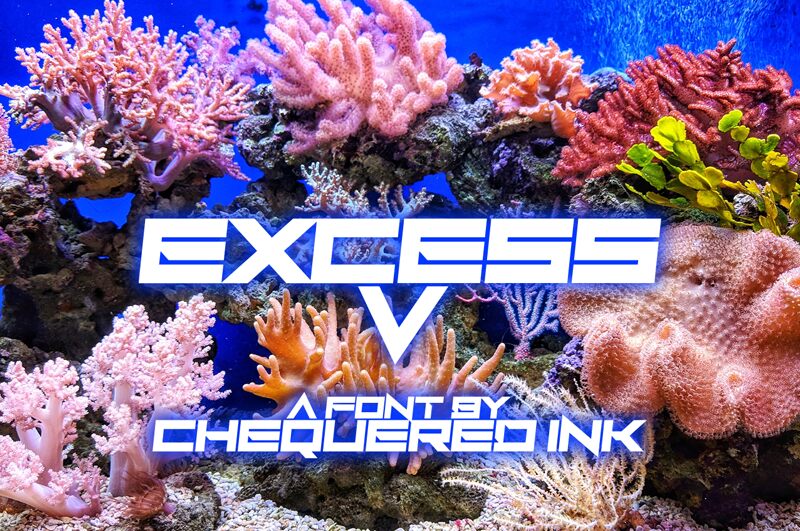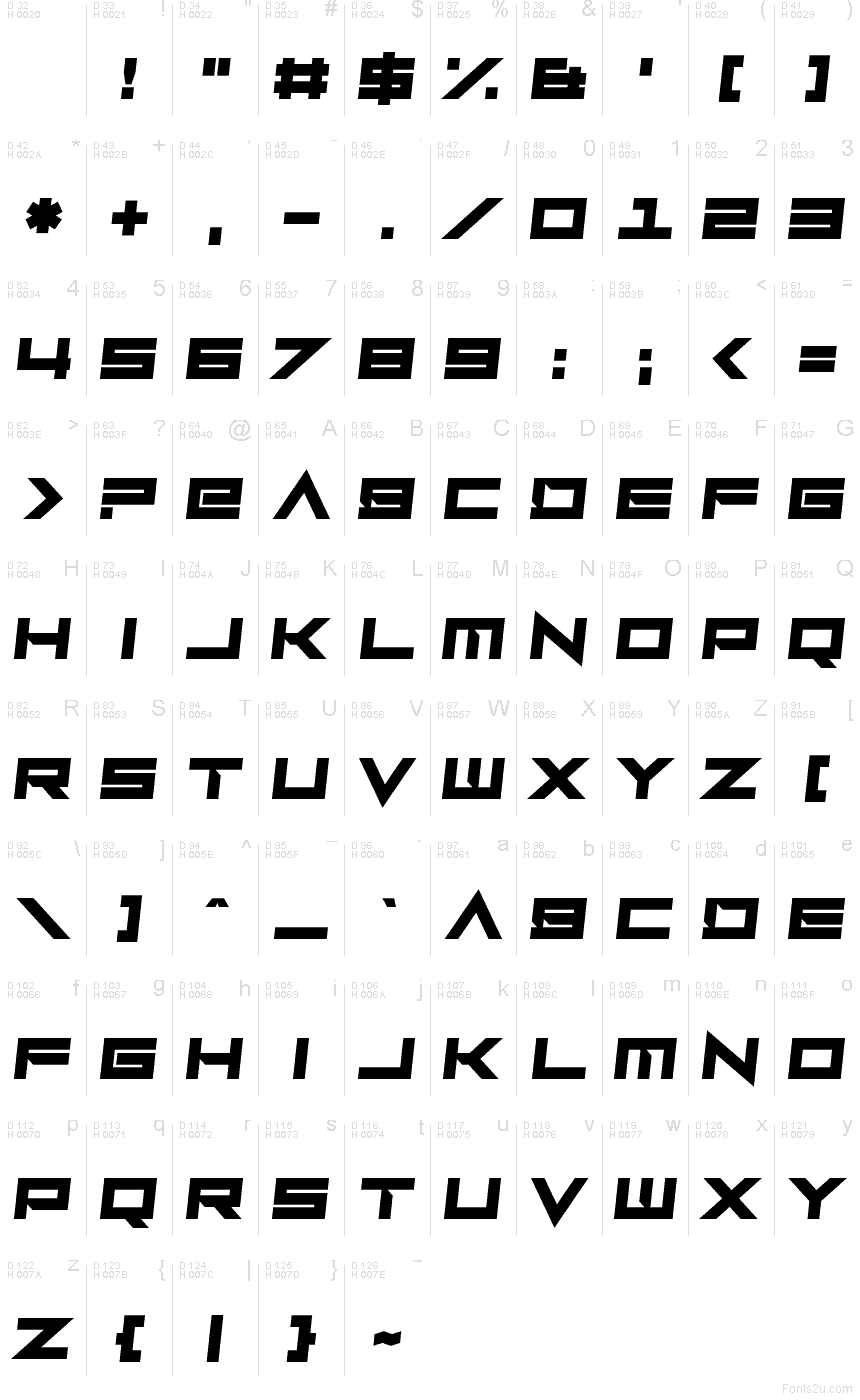
Excess V od Chequered Ink je bezplatné techno display písmo s tvrdým, inžinierskym charakterom. Veľké písmená pôsobia ako vytesané z masívnych blokov, s ostrými zárezmi a dlhými horizontálnymi rezmi, ktoré im dodávajú rýchly, modulárny a mierne strohý vzhľad.
Hodí sa na plagáty, sci-fi branding, herné logá, letáky či obálky, kde je potrebné vyjadriť futuristický štýl bez zbytočnej dekoratívnosti. Využite ho na krátke nadpisy alebo monogramy, pretože hlboké diagonálne rezy dodávajú aj krátkym slovám nabitý, mechanický rytmus.
Prezentácia a vizuálna ukážka písma Excess V
Mapa znakov písma Excess V
Mapa znakov písma Excess V: Základná latinka, strana 1
Glyfy písma Excess V — Základná latinka, strana 1